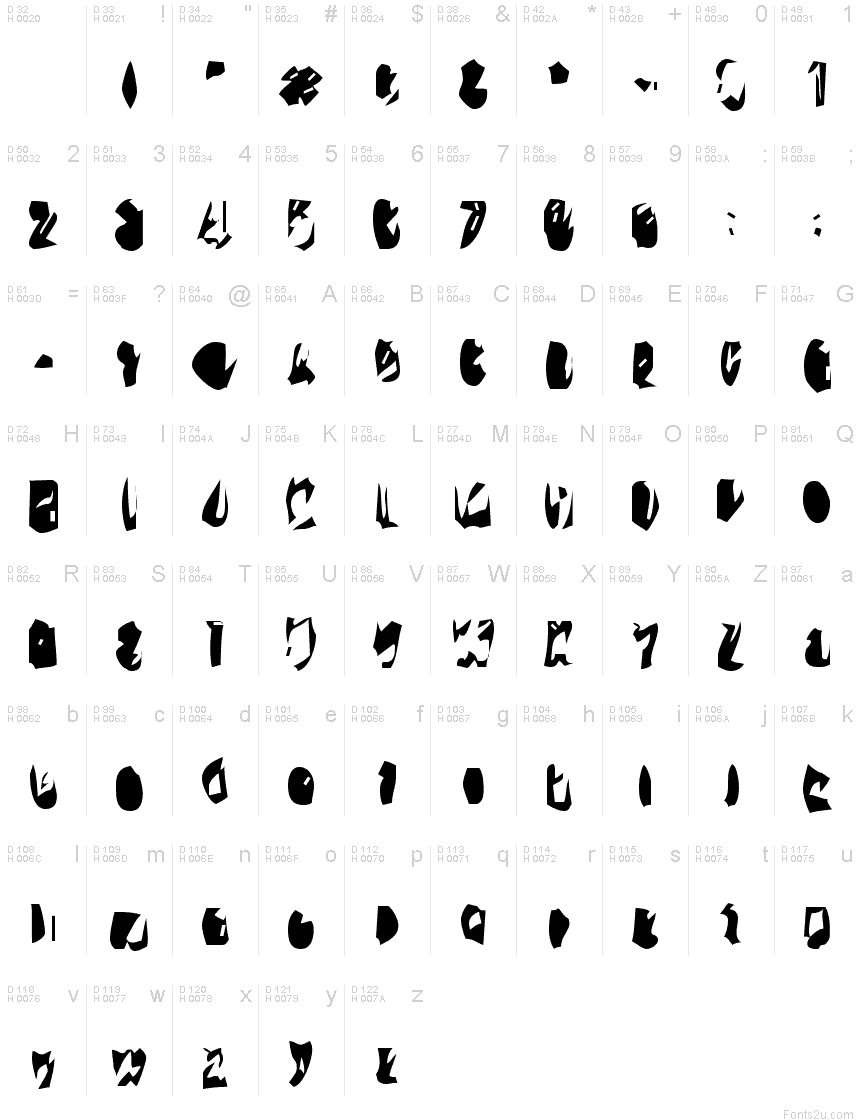
15teen od Tommyho Caryho je bezplatné, deformované titulkové písmo, které působí jako ručně vyřezaná šablona vtažená do mokrého inkoustu. Jeho masivní tvary bobtnají a deformují se, jako by se roztékaly na stránce, a ostré vnitřní výřezy působí spíše jako seknutí než jako klasické vnitřní tvary. Výsledkem je hlučný, nespoutaný a trochu chaotický vzhled – přesně ta energie, kterou hledáte, když čistá a uhlazená typografie prostě nestačí.
S písmem 15teen vaše nadpisy zaujmou tak, jako když se značka fixkou vryje do betonové zdi. Toto bezplatné písmo je ideální pro plakáty na koncerty, hororové tituly, undergroundové ziny, branding skate nebo streetwear značek, obaly alb či grunge grafiku na sociální sítě. Používejte ho ve velkém a pro hlavní text ho zkombinujte s jednoduchým bezpatkovým písmem, aby divoké tvary 15teen zůstaly čitelné a úderné.